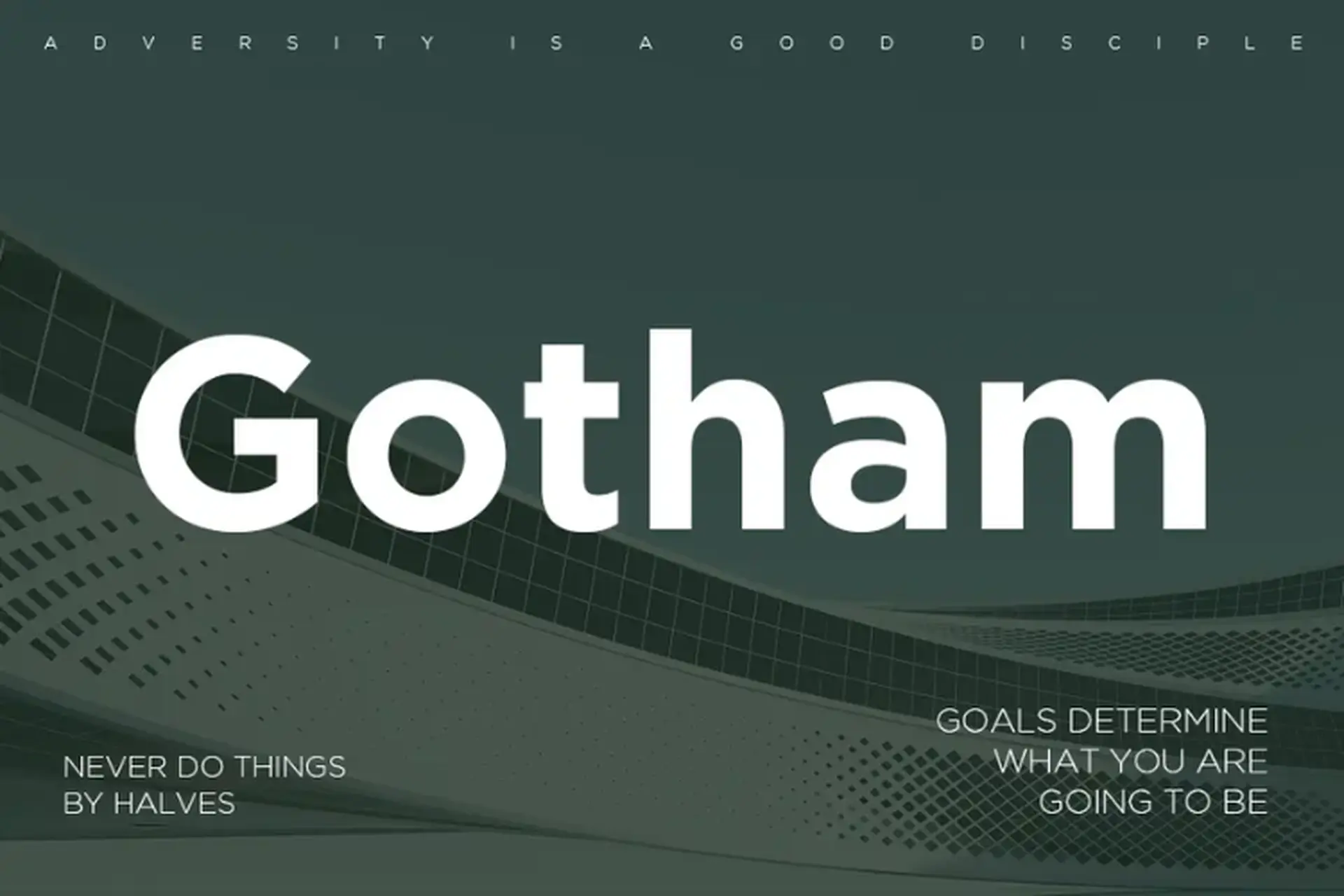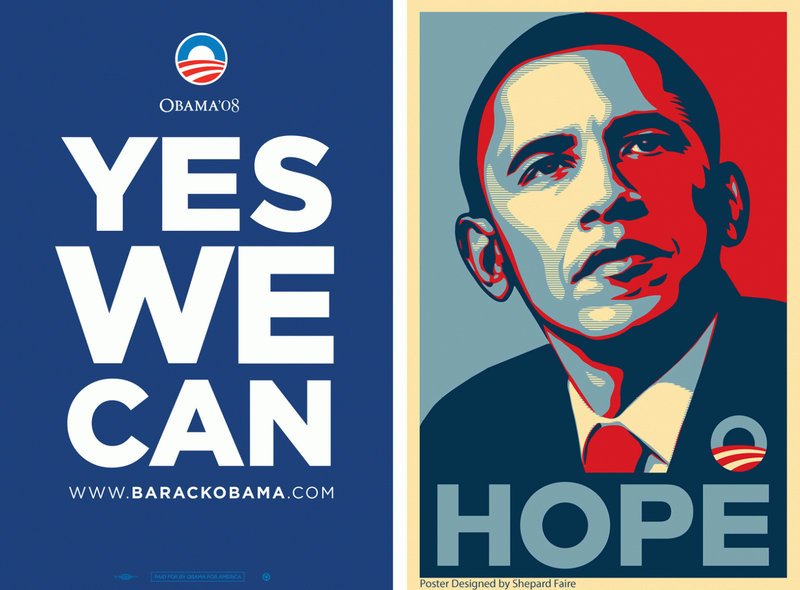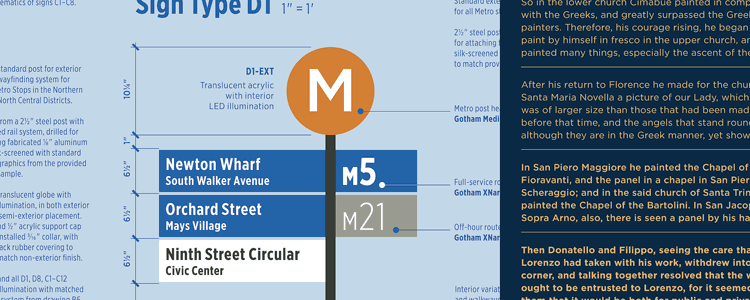
Ra đời năm 2000, font Gotham lấy cảm hứng từ biển hiệu New York cổ điển và nhanh chóng trở thành lựa chọn hàng đầu cho thương hiệu và truyền thông. Trong bài viết này, hãy cùng khám phá nguồn gốc, sức ảnh hưởng và lý do font Gotham được sử dụng rộng rãi trong thiết kế ngày nay.
Ra đời từ nhịp sống năng động của New York, Gotham font mang trong mình tinh thần thẳng thắn và hiện đại của nước Mỹ. Không cầu kỳ hay kiểu cách, font chữ này gây ấn tượng bởi sự rõ ràng, tự tin và chuyên nghiệp, những yếu tố giúp nó trở thành "ngôn ngữ hình ảnh" quen thuộc trong báo chí, quảng cáo và thiết kế thương hiệu ngày nay.
Font Gotham là gì?
Gotham là một kiểu chữ sans-serif hiện đại được thiết kế bởi Jonathan Hoefler và Tobias Frere-Jones vào năm 2000 tại Hoefler Type Foundry. Font được lấy cảm hứng từ biển hiệu và kiến trúc New York giữa thế kỷ 20, mang phong cách hình học cân đối, rõ ràng và mạnh mẽ. Với các đường nét đơn giản nhưng tinh tế, Gotham thể hiện sự chân thực, hiện đại và đáng tin cậy, khác biệt so với các font sans-serif truyền thống như Helvetica hay Futura. Nó kết hợp hoàn hảo giữa tính kỹ thuật của Geometric và cảm xúc của Grotesque, tạo nên vẻ đẹp vừa chính xác vừa gần gũi.
Font Gotham ra đời từ niềm say mê của Jonathan Hoefler với những dòng chữ sans-serif giản dị, trung thực và mạnh mẽ từng xuất hiện trên biển hiệu, tòa nhà và bản đồ khắp New York giữa thế kỷ 20. Đó là kiểu chữ không mang tên, không thuộc về bất kỳ font nào, chỉ tồn tại trong nhịp sống đô thị, thô mộc nhưng tinh tế.
Năm 1992, Hoefler thử sức với bản nháp Typeface X, kết hợp hai phong cách Grotesque và Geometric nhằm tìm ra giọng điệu riêng. Tuy nhiên, dự án sớm bị dừng lại vì hạn chế kỹ thuật và hiệu ứng thị giác chưa đạt. Đến năm 1994, khi ông bắt gặp biển hiệu "Port Authority Bus Terminal" ở New York - mẫu chữ thể hiện trọn vẹn tinh thần mà mình theo đuổi, ý tưởng về Gotham mới thật sự hình thành rõ nét.
Năm 1999, Hoefler hợp tác cùng Tobias Frere-Jones tại Hoefler Type Foundry. Khi tạp chí GQ đặt hàng một kiểu chữ sans-serif mang vẻ đẹp hiện đại và tinh gọn, họ đã phát triển thiết kế dựa trên phong cách chữ của Port Authority. Năm 2000, Gotham chính thức ra đời như một kiểu chữ có cấu trúc hình học cân đối, trung tính nhưng tràn đầy sức sống đô thị. Nó vừa là kết tinh tinh thần của New York, vừa là minh chứng cho sự hòa quyện giữa nghệ thuật thủ công và thiết kế hiện đại.
Sau khi ra mắt, font Gotham nhanh chóng được phát triển thành một họ chữ hoàn chỉnh với nhiều biến thể như Condensed, Narrow, Rounded cùng các cấp độ đậm nhạt đa dạng. Font xuất hiện rộng rãi trong báo chí, quảng cáo và nhận diện thương hiệu toàn cầu. Đặc biệt, font Gotham được sử dụng trong chiến dịch tranh cử của Barack Obama năm 2008, đã trở thành biểu tượng của niềm tin, sự thay đổi và tinh thần tiến bộ trong thiết kế truyền thông.
Mở rộng và ảnh hưởng
Năm 2011, Bảo tàng Nghệ thuật Hiện đại New York (MoMA) chính thức đưa Gotham vào bộ sưu tập thiết kế vĩnh viễn. Font Gotham không chỉ là một kiểu chữ mà còn là biểu tượng của tinh thần Mỹ đương đại, xuất hiện phổ biến từ biển hiệu đường phố đến tòa nhà chọc trời, từ tạp chí thời trang đến Nhà Trắng. Hơn hai thập kỷ sau khi ra đời, Gotham vẫn giữ vị thế của một kiểu chữ của thời đại số, mang trong mình linh hồn của thành phố nơi nó được sinh ra.
Hơn hai thập kỷ trôi qua, font Gotham vẫn giữ vị thế đặc biệt trong thế giới typography. Nó không chỉ là lựa chọn của các nhà thiết kế mà còn là minh chứng cho cách một kiểu chữ có thể định hình cảm xúc, phong cách và bản sắc thương hiệu. Từ New York hoa lệ đến mọi không gian sáng tạo, Gotham vẫn là biểu tượng của sự bền vững và tinh tế vượt thời gian.